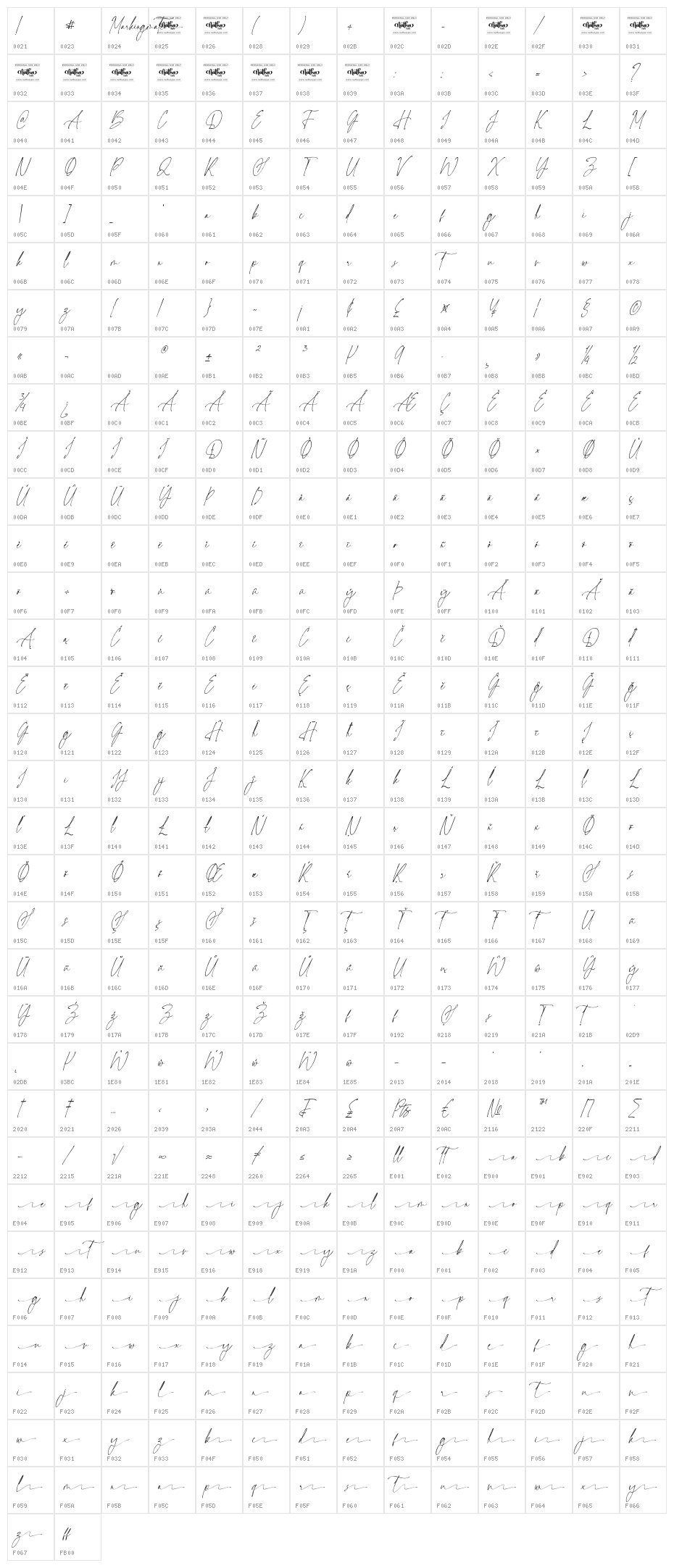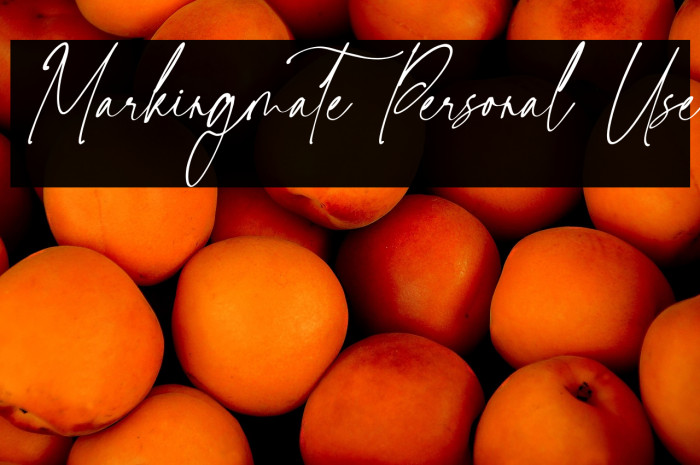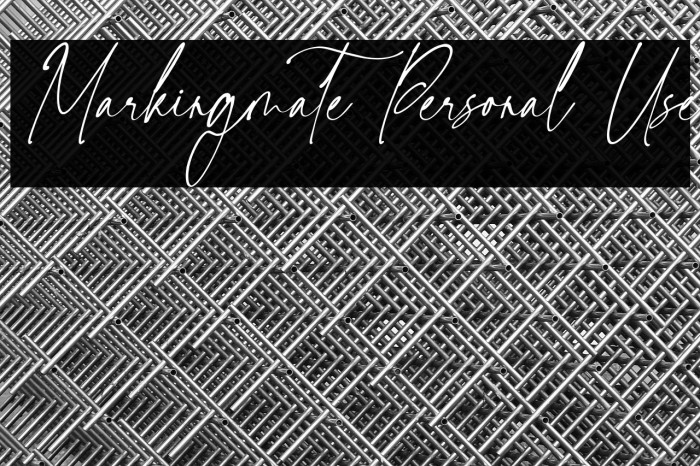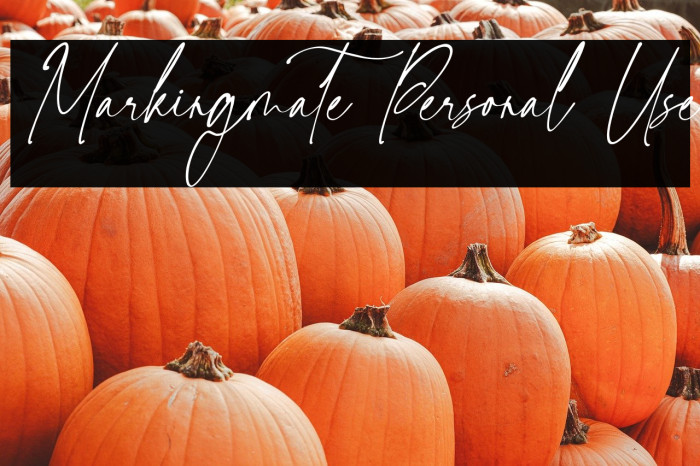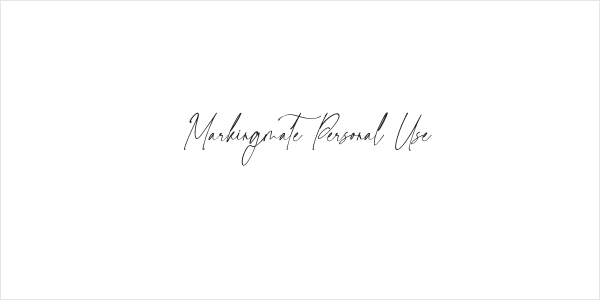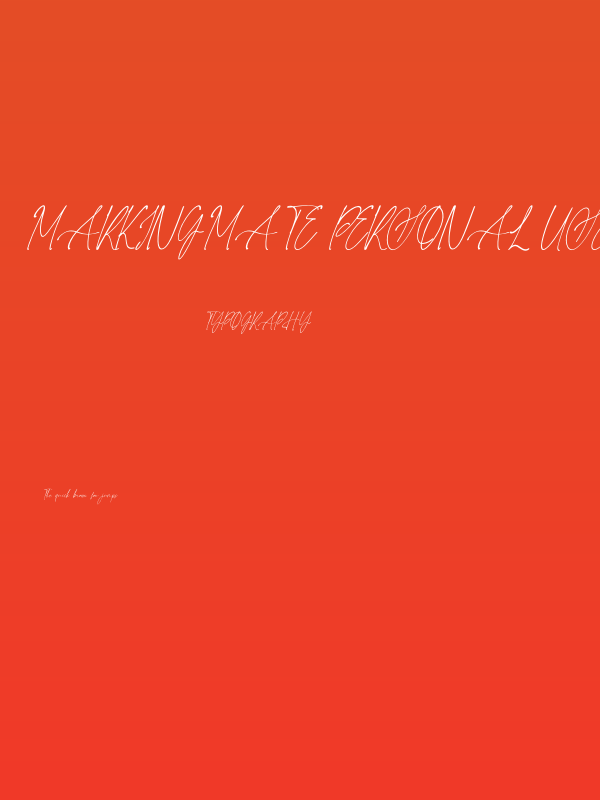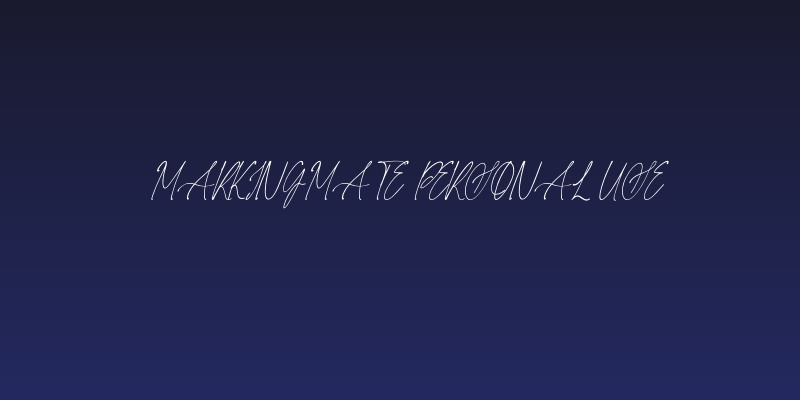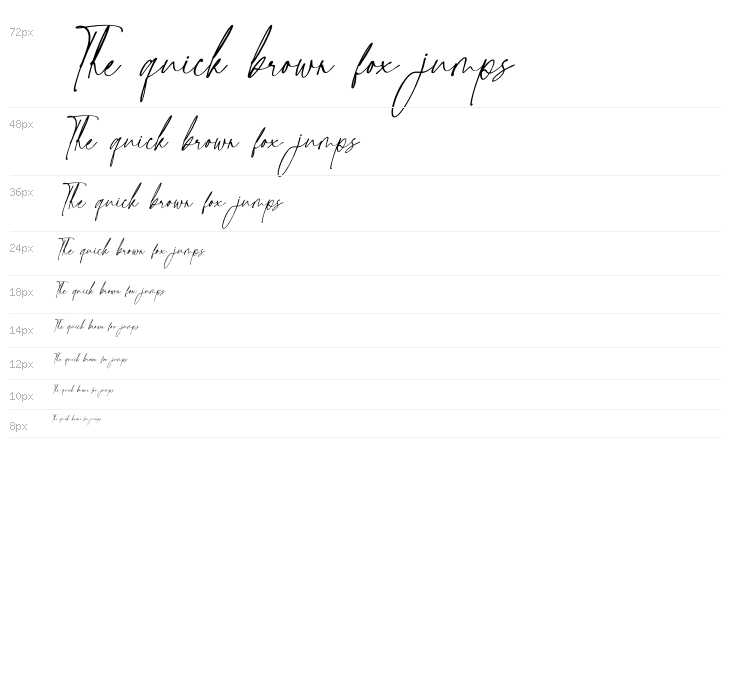
Markingmate Personal Use Font
| Caso d'uso | Logos, Invitations, Artistic projects |
| Progetti proposti | Ideal for wedding invitations, greeting cards, branding, and logo design. |